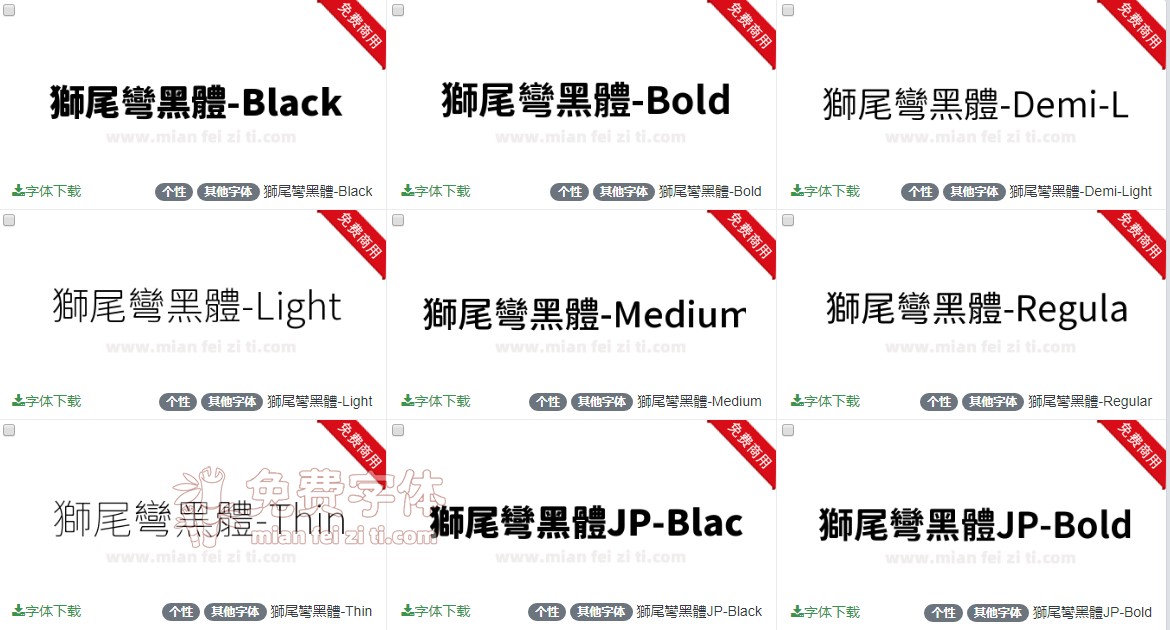
狮尾弯黑体:思源黑体变圆和拔脚改造免费商用字体资讯
狮尾弯黑体基于思源黑体的变圆和拔脚改造,更加简明现代化的字体。支援简体中文、繁体中文、韩文与日文;可以免费商用,欢迎大家自由应用、自由优化、自由改作!
狮尾弯黑体」与「狮尾圆体」的主要差别在笔触是否有做调整,狮尾弯黑体所套用的效果较少,在笔触没有做调整。